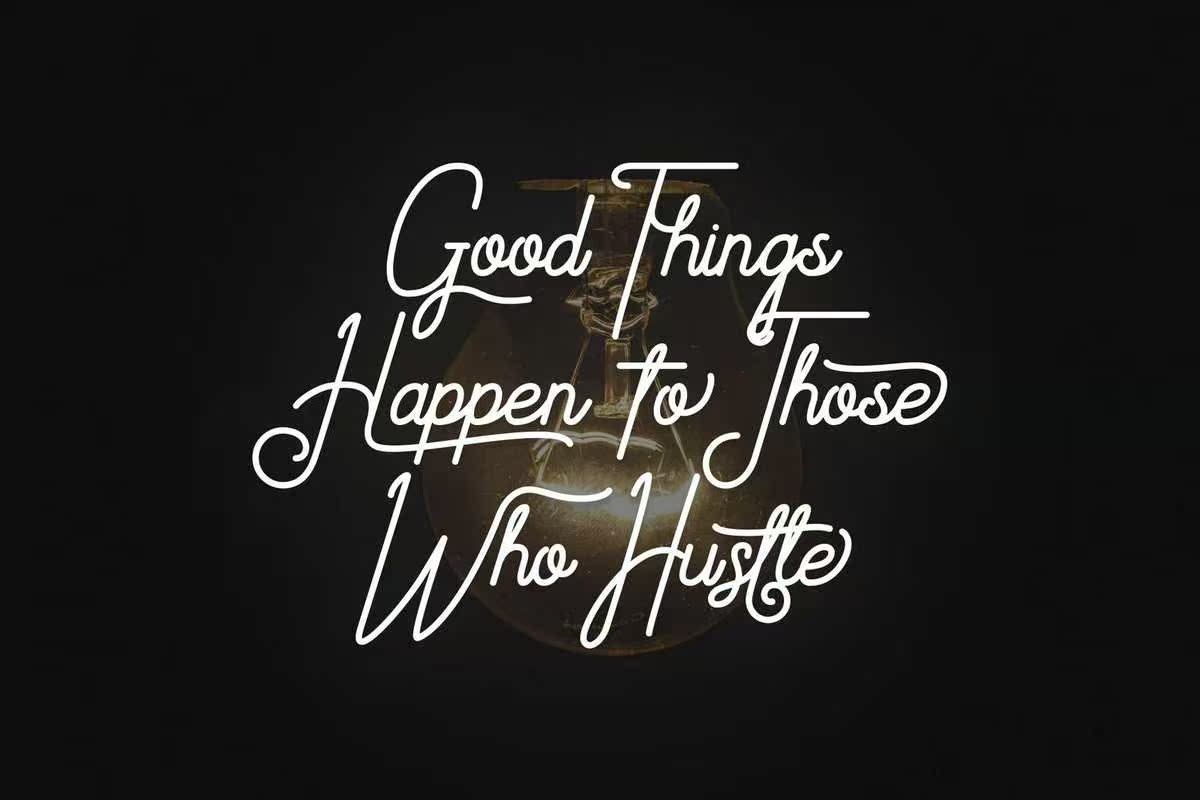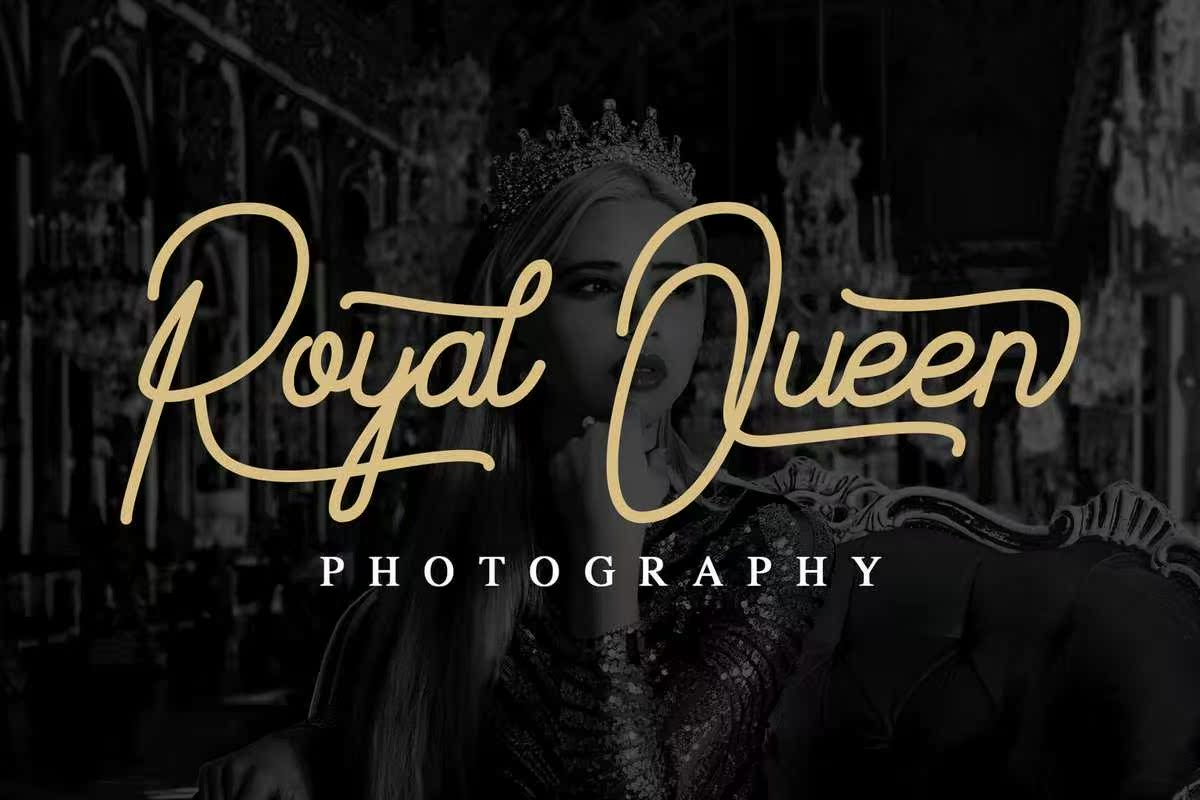
Archestry Monoline Scription是一款手工设计的线条,外观粗犷、厚重、复古。具有年份特征,Archestry字体适用于徽标、社交媒体、广告、产品包装、产品设计、标签、照片、水印、邀请函、,文具商和其他任何需要使用AbrushStyleFont或简单的文本覆盖在任何背景图像或QuoteImages上的项目。ArchestRyMonoline脚本是手工制作的Demonoline Font,具有粗体、厚重和复古的外观样式。由于其年份特征,Archestry字体适用于徽标、社交媒体、广告、产品包装、产品设计、标签、,照片、水印、邀请函、文具和其他任何需要AbrushStyleFontor的项目,或者简单地在任何背景图像或QuoteImages上覆盖Astylish文本。